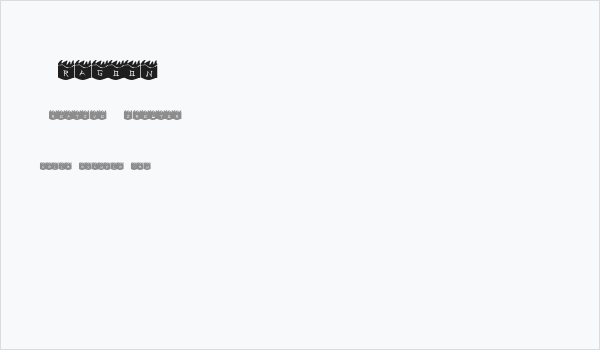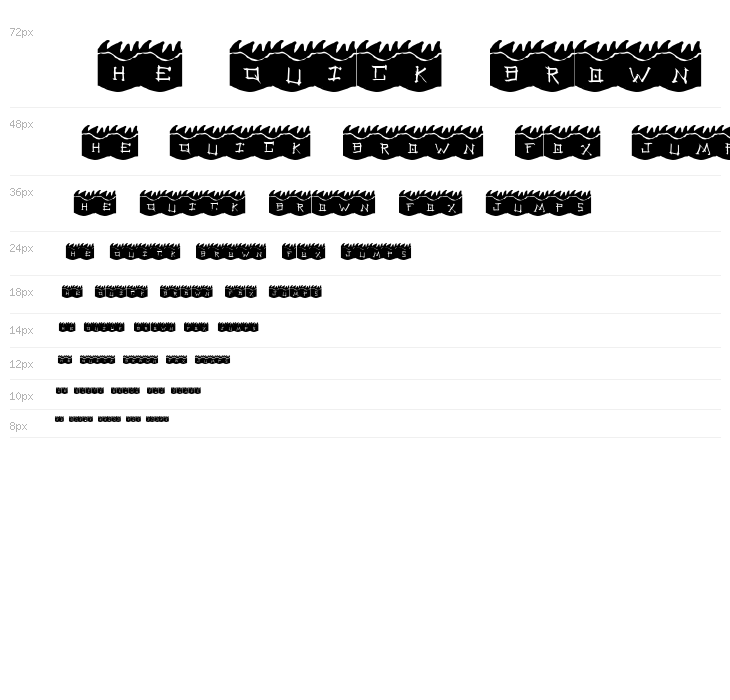
Dragoon Font
| Progetti proposti | Perfect for fantasy book covers, game titles, themed event posters, or any project needing a dramatic, medieval touch. |